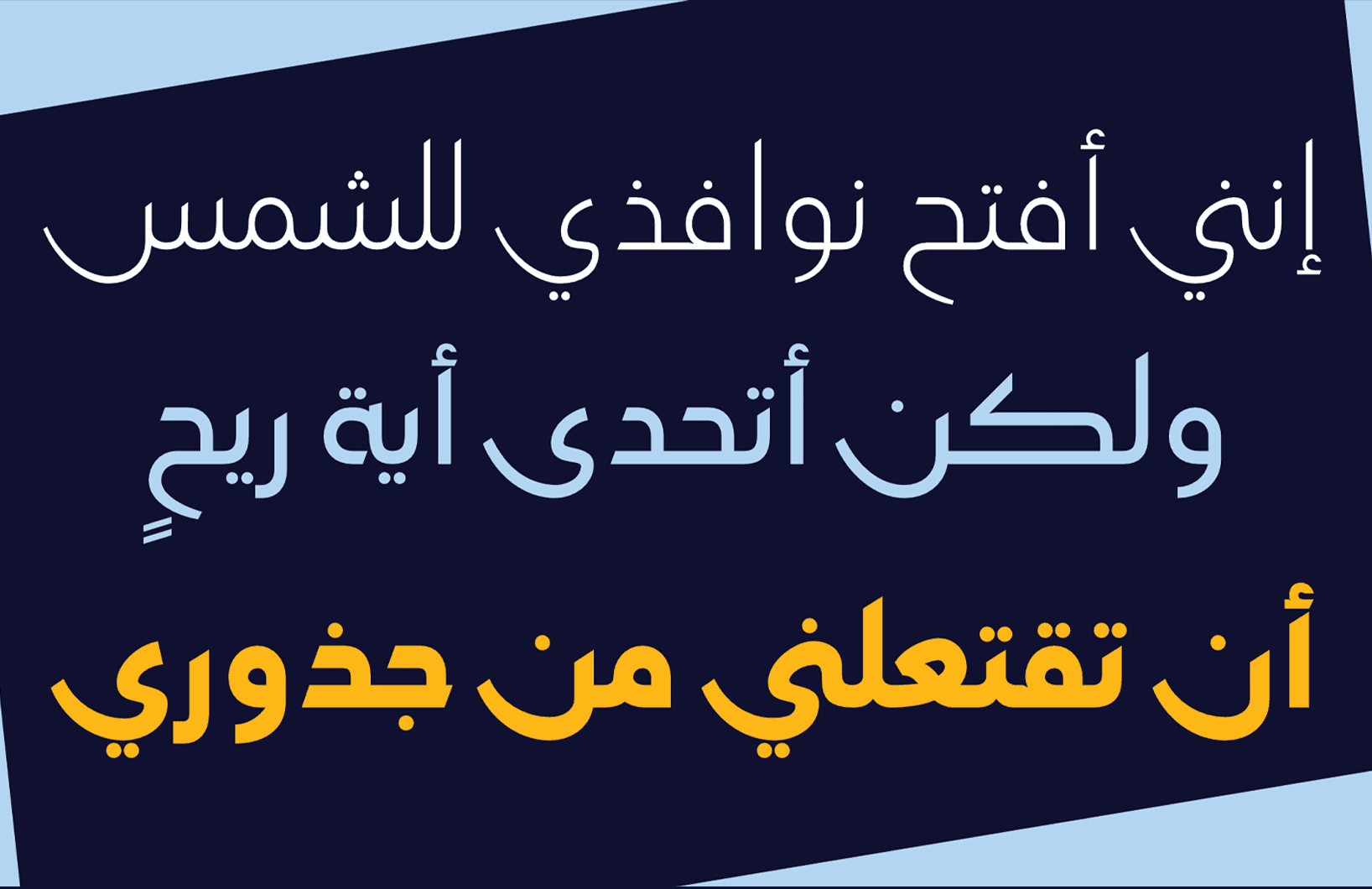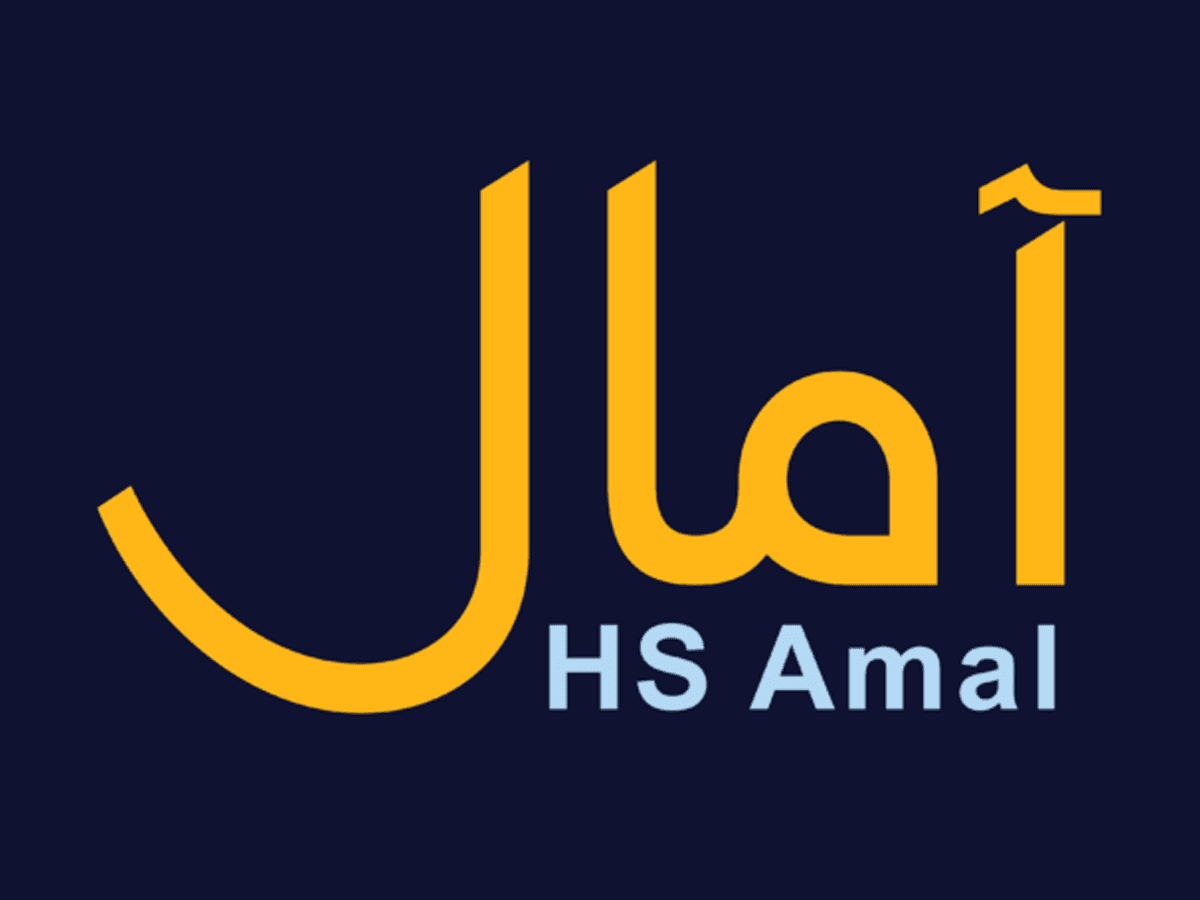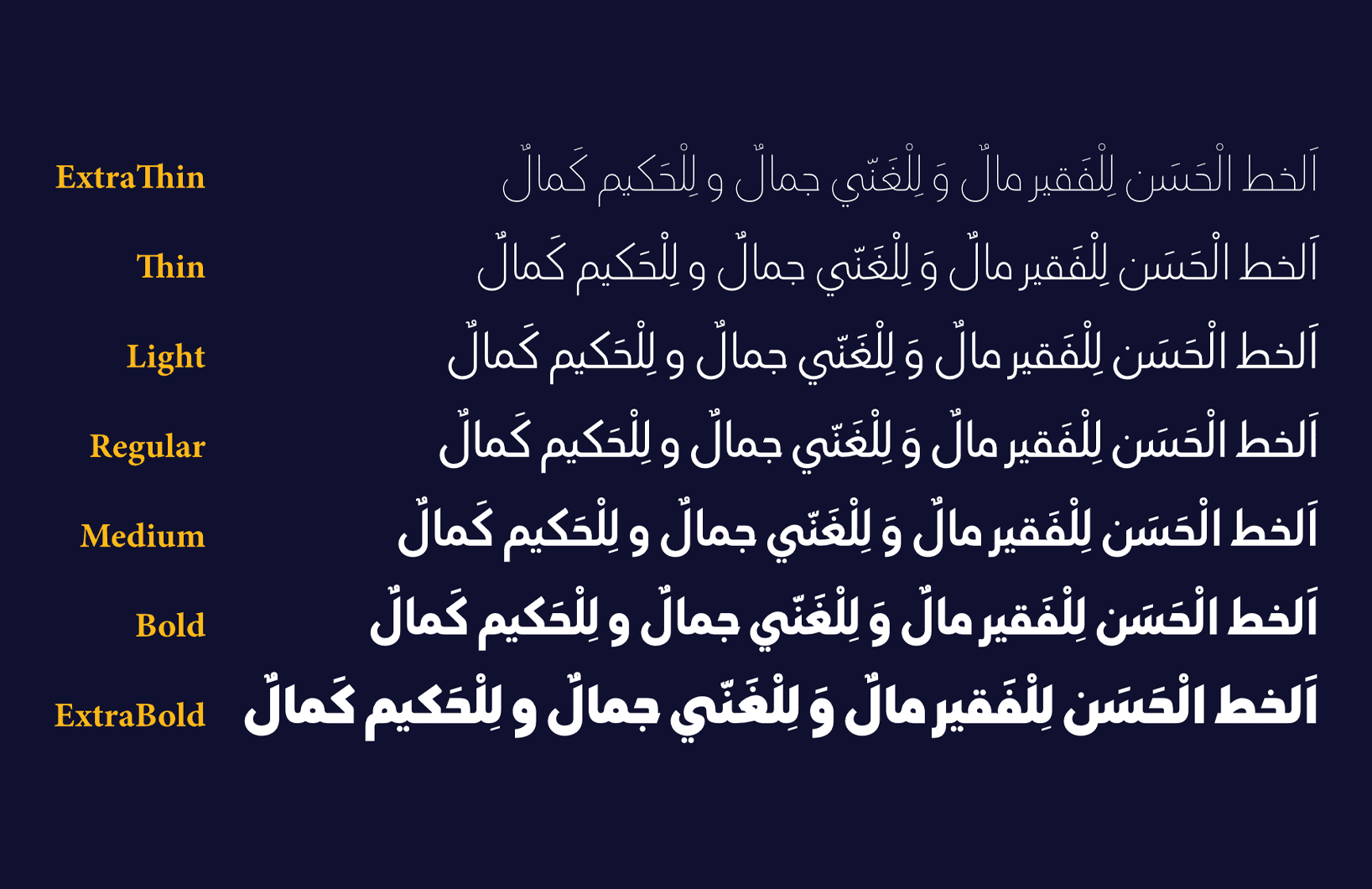
تم إصدار النسخة الأولى من الخط الطباعي «حسن آمال» في عام 2008 لتقديم حرف طباعي عربي حديث من نوع أوبن تايب، يجمع ما بين خصائص الخط الكوفي والنسخ، وتتمتع أجزاء حروفه بالاستدارة أو الاستقامة، إضافة إلى الليونة التي جعلت منه خطاً سهل القراءة. «حسن آمال» هو حرف طباعي يمكن استخدامه في كتابة كلا من العناوين أو النصوص في المشاريع الجرافيكية والنشرية الحديثة، وهو يدعم اللغة العربية والفارسية والأردية ويحتوي على ثلاثة أوزان وهي: الخفيف، والعادي، والأسود.